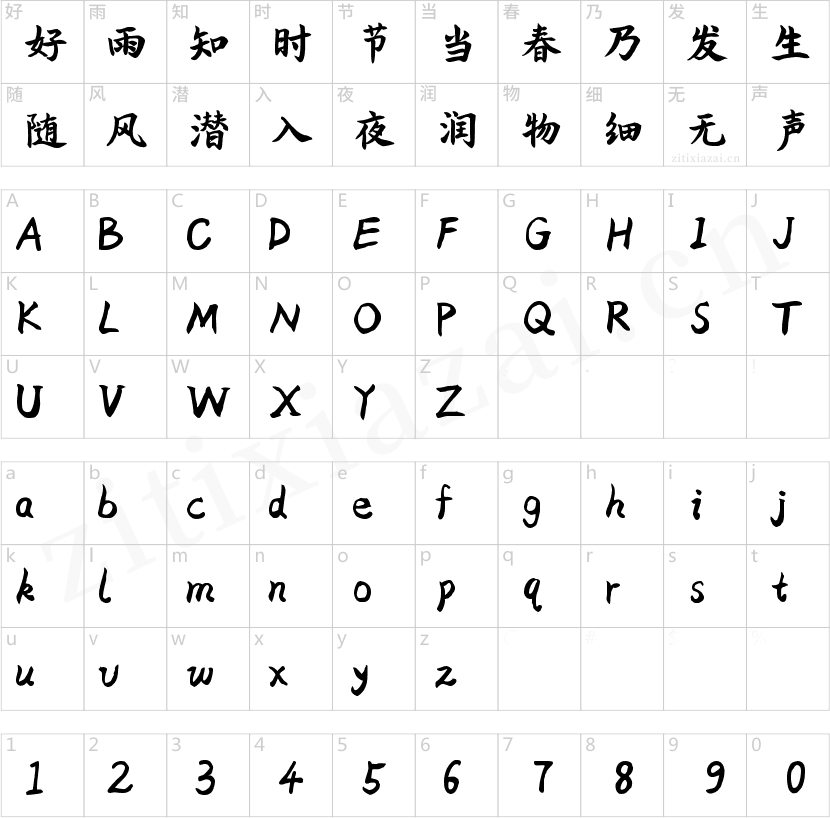
Aa语文老师的字
Aa语文老师的字字体
Aa语文老师的字是一款非常具有艺术性的字体,它的设计灵感来源于对古典艺术的研究,同时又融入了现代字体设计的元素。字形优美,笔画粗细变化自然,给人以大气、典雅的感觉。Aa语文老师的字是一款既传统又现代的字体,它的设计充满艺术感,美观大方,实用性也非常强。无论是对于设计师还是对于普通读者来说,都是一种非常不错的字体选择。Aa语文老师的字适合用于具有艺术感的场合,比如海报、宣传单张、书籍封面等。由于其字形流畅且具有动态感,也适合用于大量的文本排版,如报纸、杂志等。